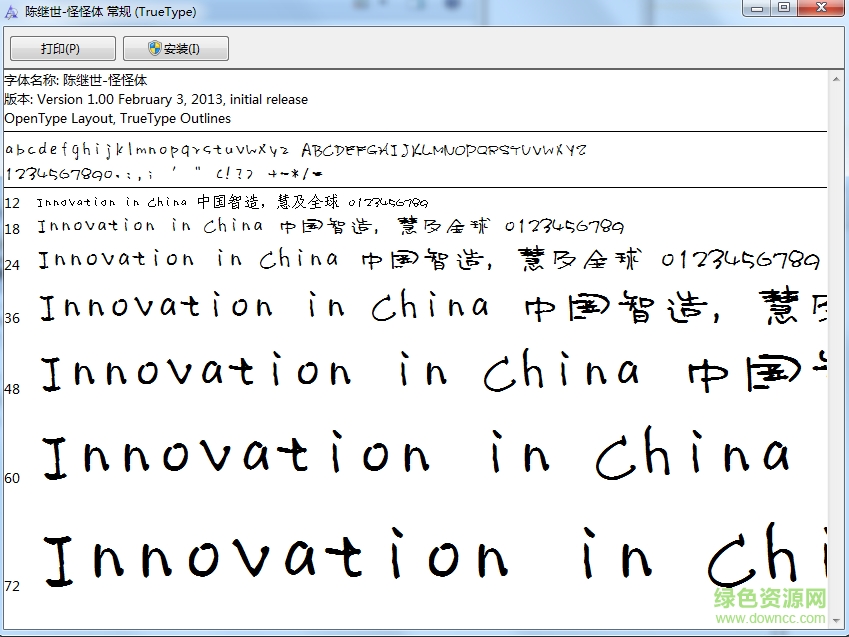
陳繼世怪怪體常規(guī)
陳繼世怪怪體是一款風(fēng)格迥異但生動活潑的藝術(shù)字體,讓你感覺與眾不同、有個性魅力的書法呈現(xiàn),采用鋼筆手寫體的模板,更顯細(xì)膩纖秀,歡迎大家來綠色資源網(wǎng)下載體驗!
陳繼世怪怪體(常規(guī))
俗話說,自認(rèn)其人,怪怪體大概就想給人一種遺世脫俗的美感吧,字跡看似毫無章法,以怪為內(nèi)涵,實則別開生面令人回味。
陳繼世怪怪字體